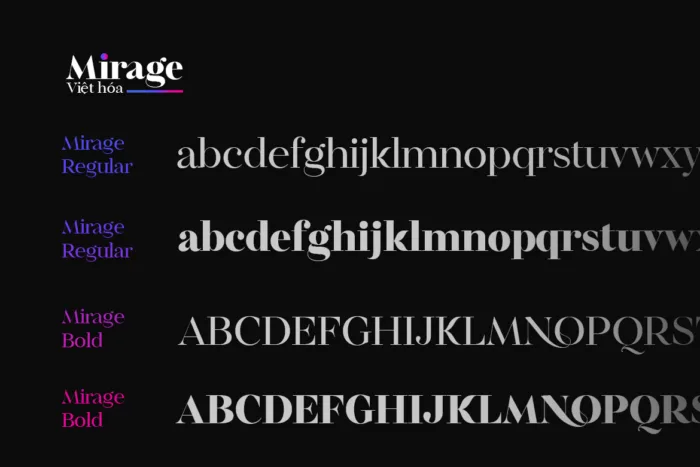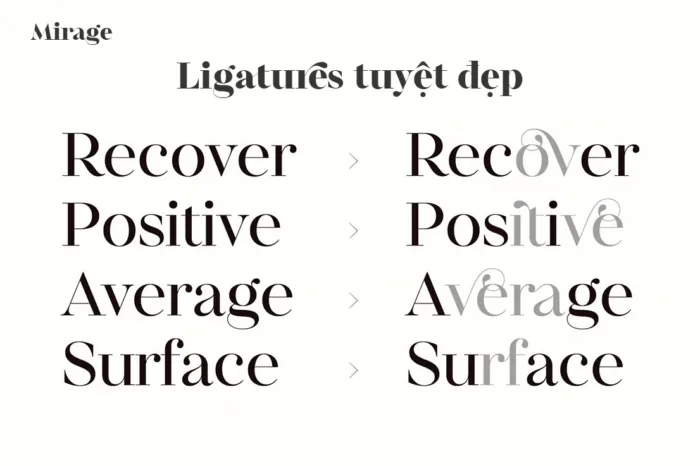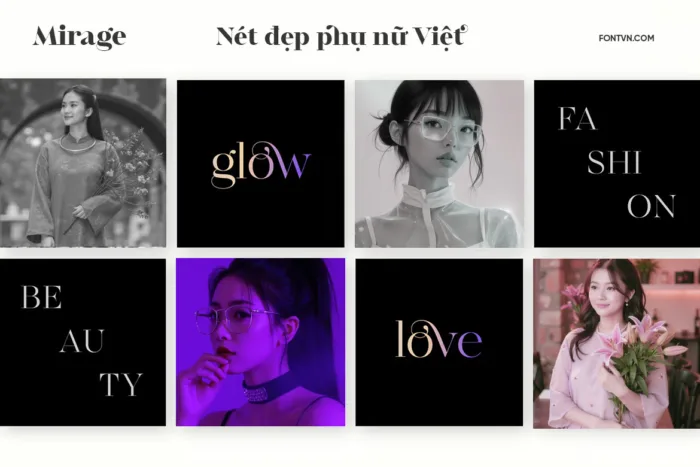
DVN Mirage Việt hóa – Font chữ Serif cao cấp (2 Style)
DVN Mirage là một kiểu chữ serif thanh lịch, mang phong cách hiện đại pha lẫn sự quyến rũ cổ điển. Với những đường nét tinh tế, các chi tiết uốn lượn nhẹ nhàng ở một số ký tự giúp font có chiều sâu và tạo điểm nhấn độc đáo. DVN Mirage phù hợp với các thiết kế mang tính sang trọng, từ thương hiệu thời trang, mỹ phẩm đến tạp chí cao cấp.
Font có sự kết hợp hài hòa giữa độ dày và độ thanh mảnh, mang đến cảm giác mềm mại nhưng vẫn giữ được độ sắc nét. Những ký tự có đuôi cong nhẹ tạo cảm giác chuyển động tự nhiên, giúp văn bản trông sống động và thu hút hơn.
DVN Mirage lý tưởng cho tiêu đề, logo và các ứng dụng thiết kế đòi hỏi sự tinh tế. Font hỗ trợ đầy đủ tiếng Việt, đảm bảo hiển thị mượt mà trên mọi nền tảng thiết kế.
Phiên bản Việt hóa gồm 2 Style: Bold và Regular
Font chữ cũng có rất nhiều chữ glyphs để bạn thay thế khi thiết kế.